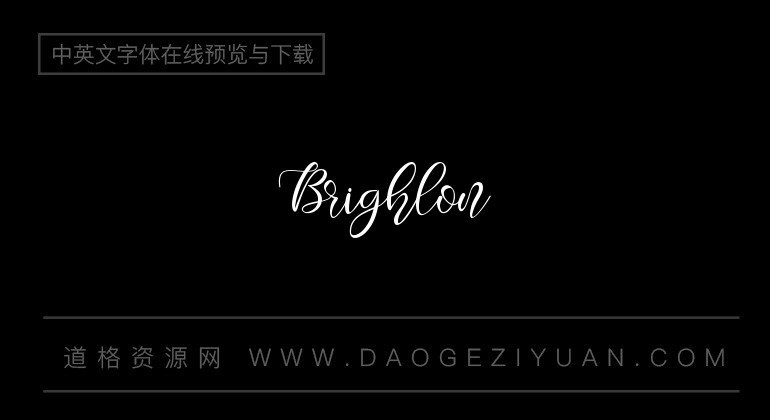
Brighlon
Brighton 字体是一款简约优雅的英文字体,由设计师Aaron Carambula设计,是一款精致的线条字体,具有轻快的笔画,有助于提升文本的可读性。它的字体特征包括细长的字母,圆形的顶部和底部,以及几何节奏的笔画组合。它的设计灵感源于经典的英国文字,并融合了现代的设计元素,是一款非常适合用于报纸,杂志,书籍,海报,网页等设计的字体。
Brighlon是一款非常不错的手写艺术字体,具有很好的视觉感,适合于文化类的宣传设计、商业类品牌的广告和产品包装设计以及个性化文字排版等较多场景。